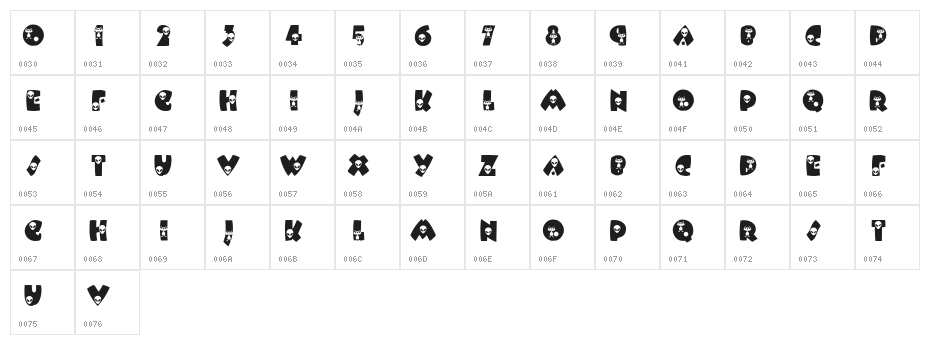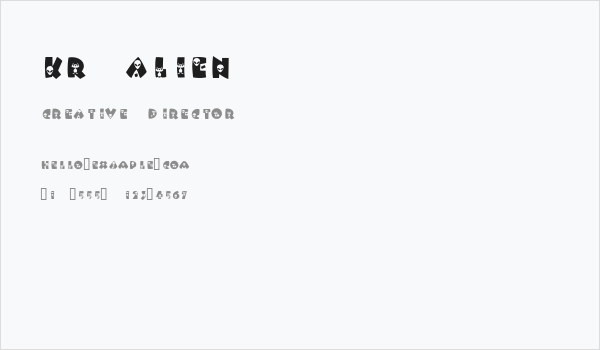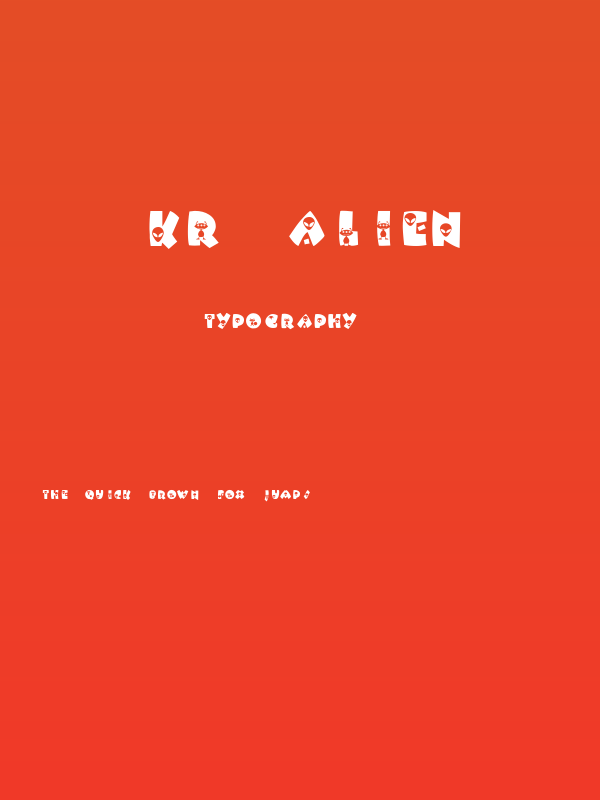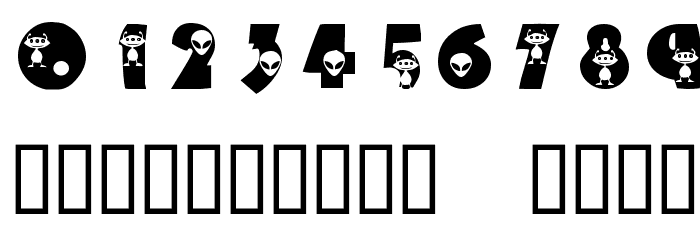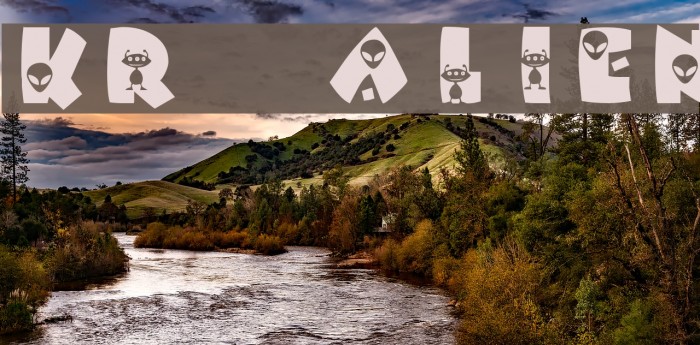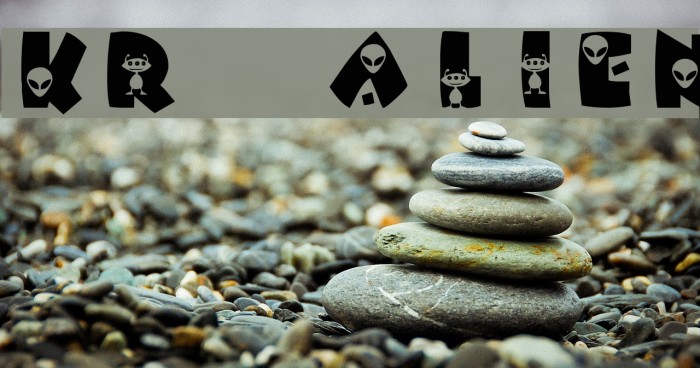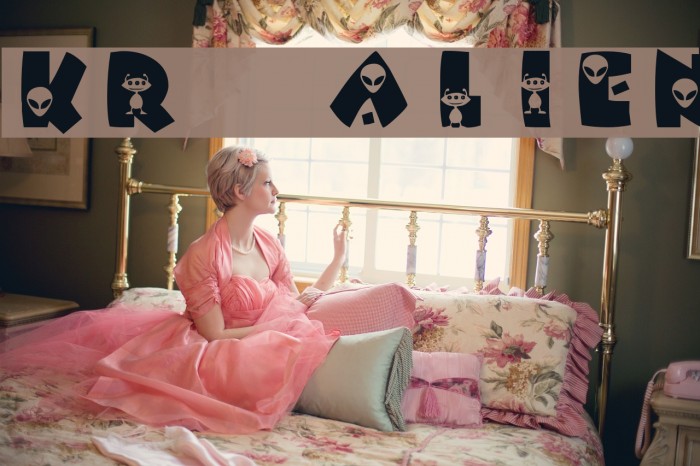
KR Alien Font
KR-ALIEN Groß
KR-ALIEN Kleinbuchstaben
KR-ALIEN Anderer Schreiben
| Vorgeschlagene Projekte | Ideal for children's book covers, sci-fi themed posters, video game graphics, and novelty merchandise. |
KR Alien